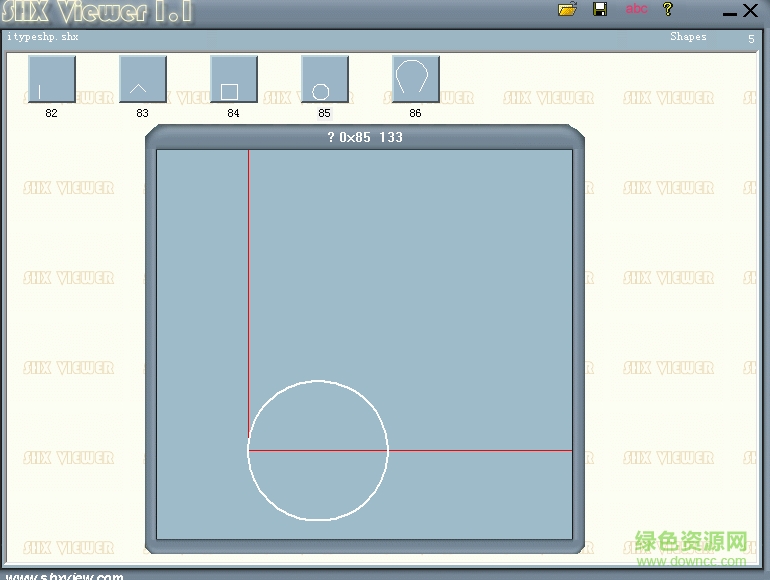
itypeshp.shx字體是一款常用的cad符號(hào)字體,本站為大家免費(fèi)提供該字體,大家找不到某種字體的時(shí)候還可以根據(jù)名字在列表中選擇一種類似的字體進(jìn)行替換使用!
符號(hào)形,顧名思義指特定符號(hào),它的一般用法有三種:
1、SHAPE實(shí)體常規(guī)使用:load命令載入,然后shape命令再指定相應(yīng)符號(hào)名稱,便加入一個(gè)SHAPE實(shí)體(常見(jiàn)的如aaa.shx)
2、嵌入線型:把符號(hào)形嵌入到線型編碼,然后實(shí)體指定該線型,便可使用(常見(jiàn)的如ltypeshp.shx)
3、特殊符號(hào):如公差符號(hào),這個(gè)是內(nèi)部使用,一般是GDT.shx
雖然都是SHX文件,不同類型字體的用途不同,肯定不能隨意替換。同類型的字體文件也不能隨意替換,即使是同名的字體文件有時(shí)內(nèi)部定義也不完全相同。例如在設(shè)計(jì)院使用較多的hztxt.shx就存在好多版本,有的帶鋼筋符號(hào),有的不帶,因此必須使用同一個(gè)版本的hztxt.shx才能保證所有字符都能正常顯示。